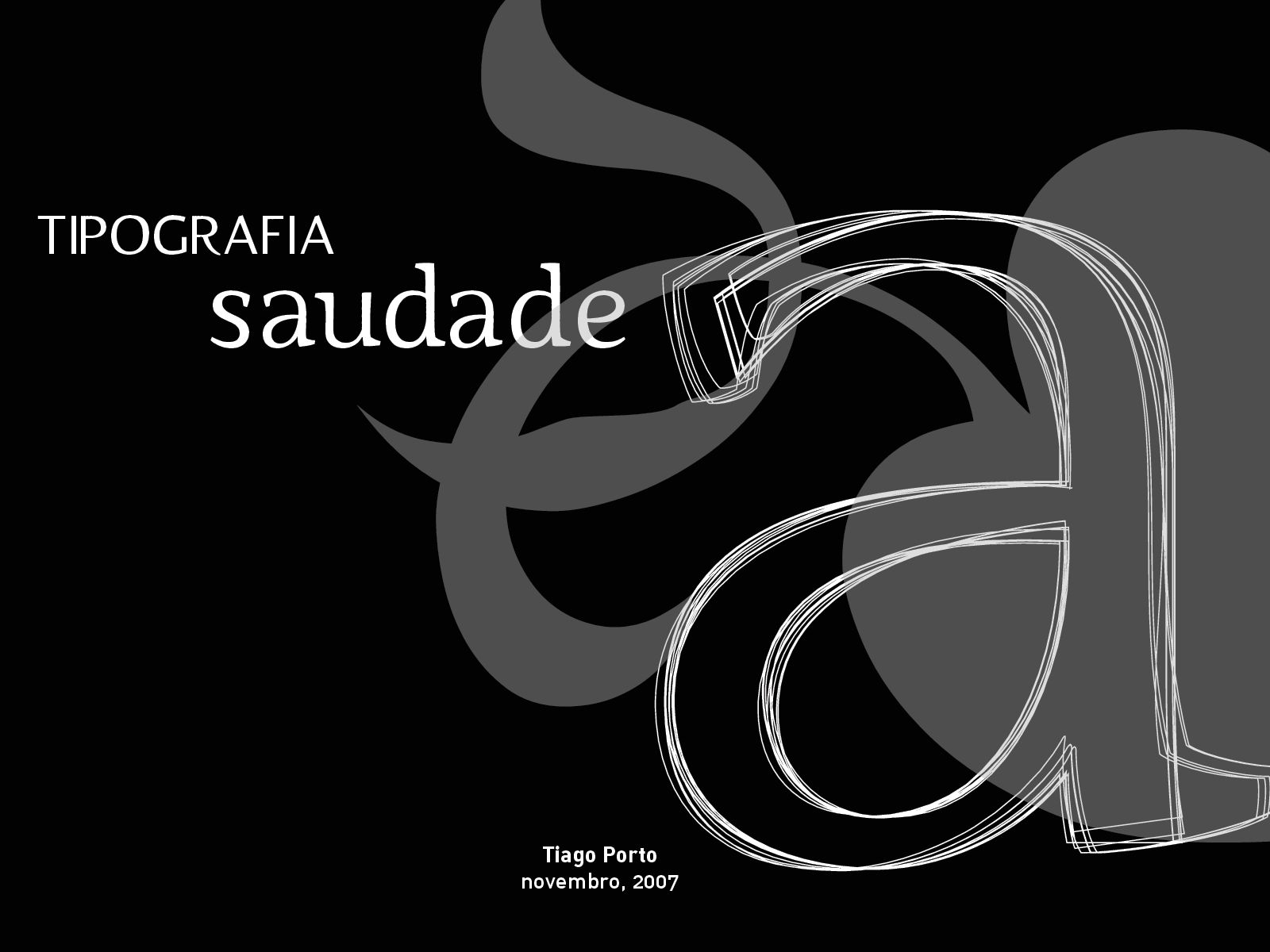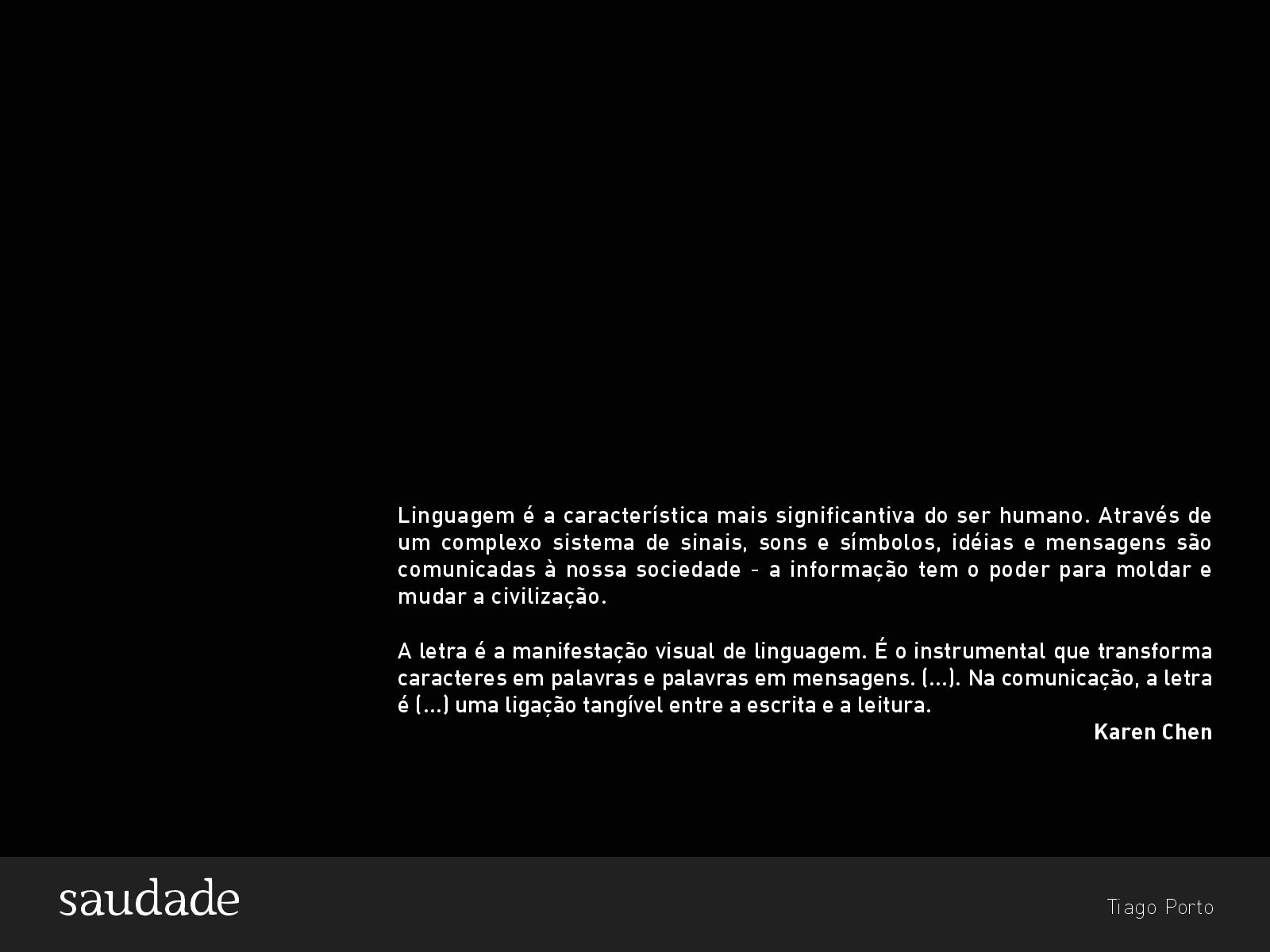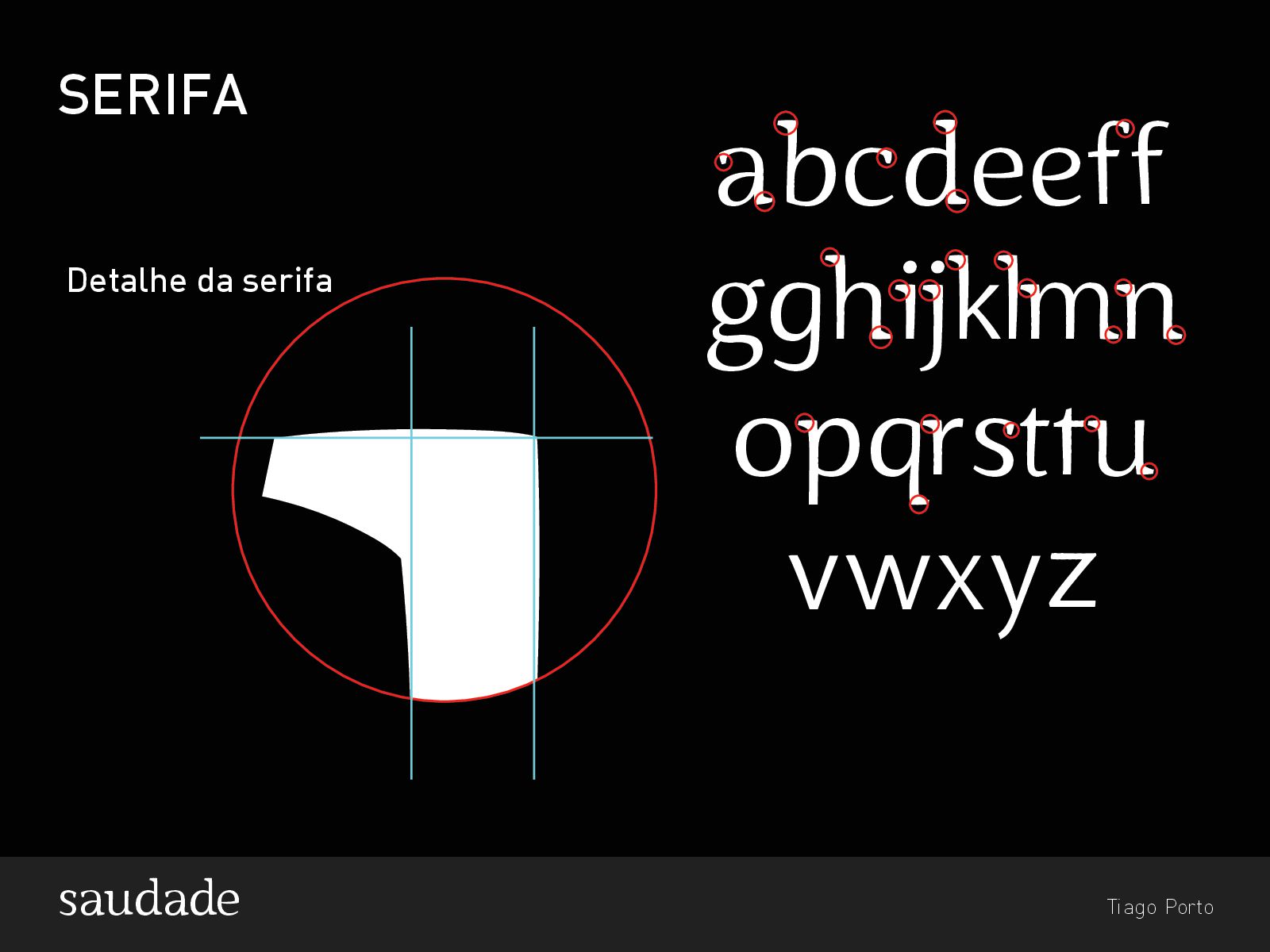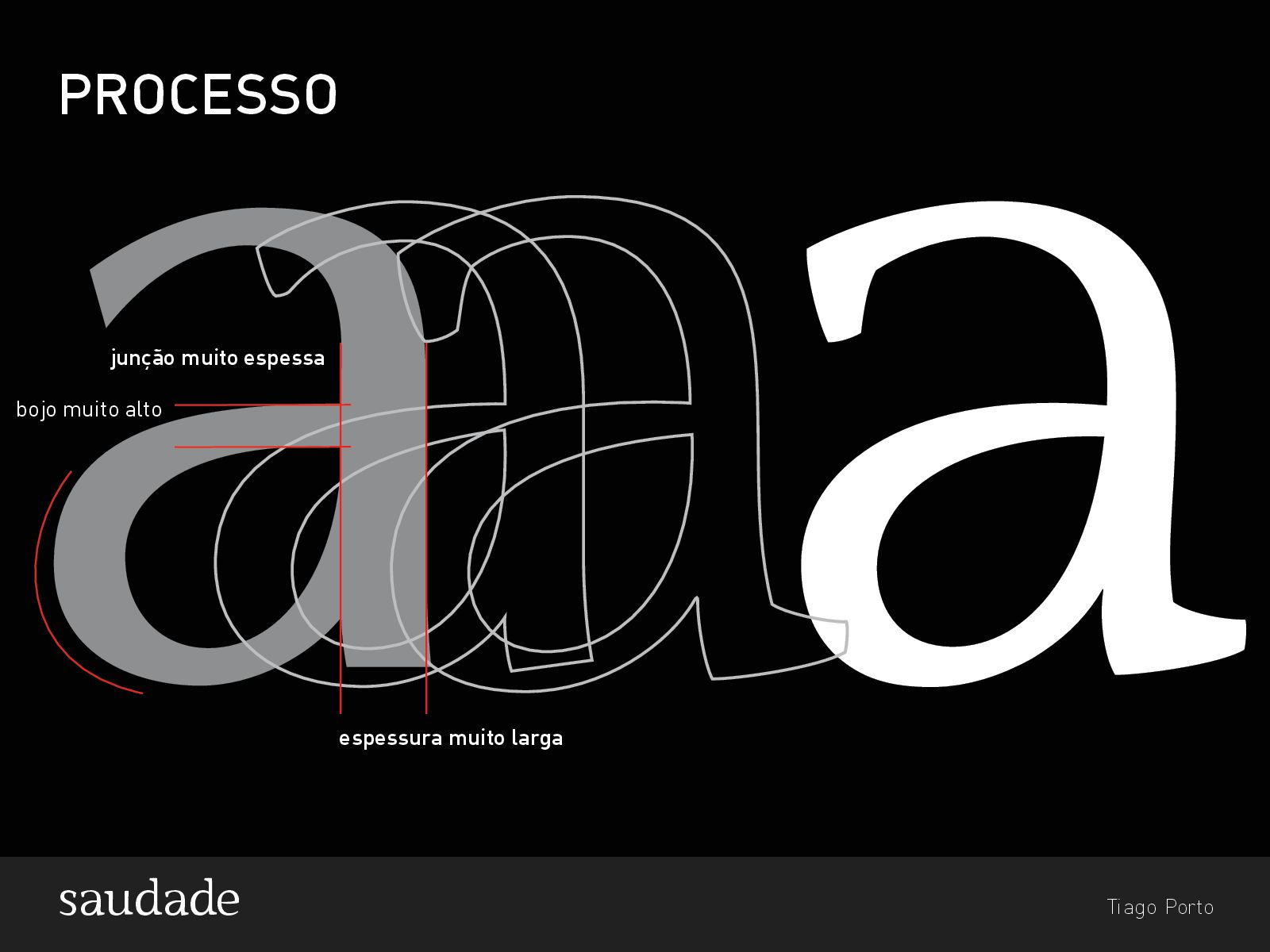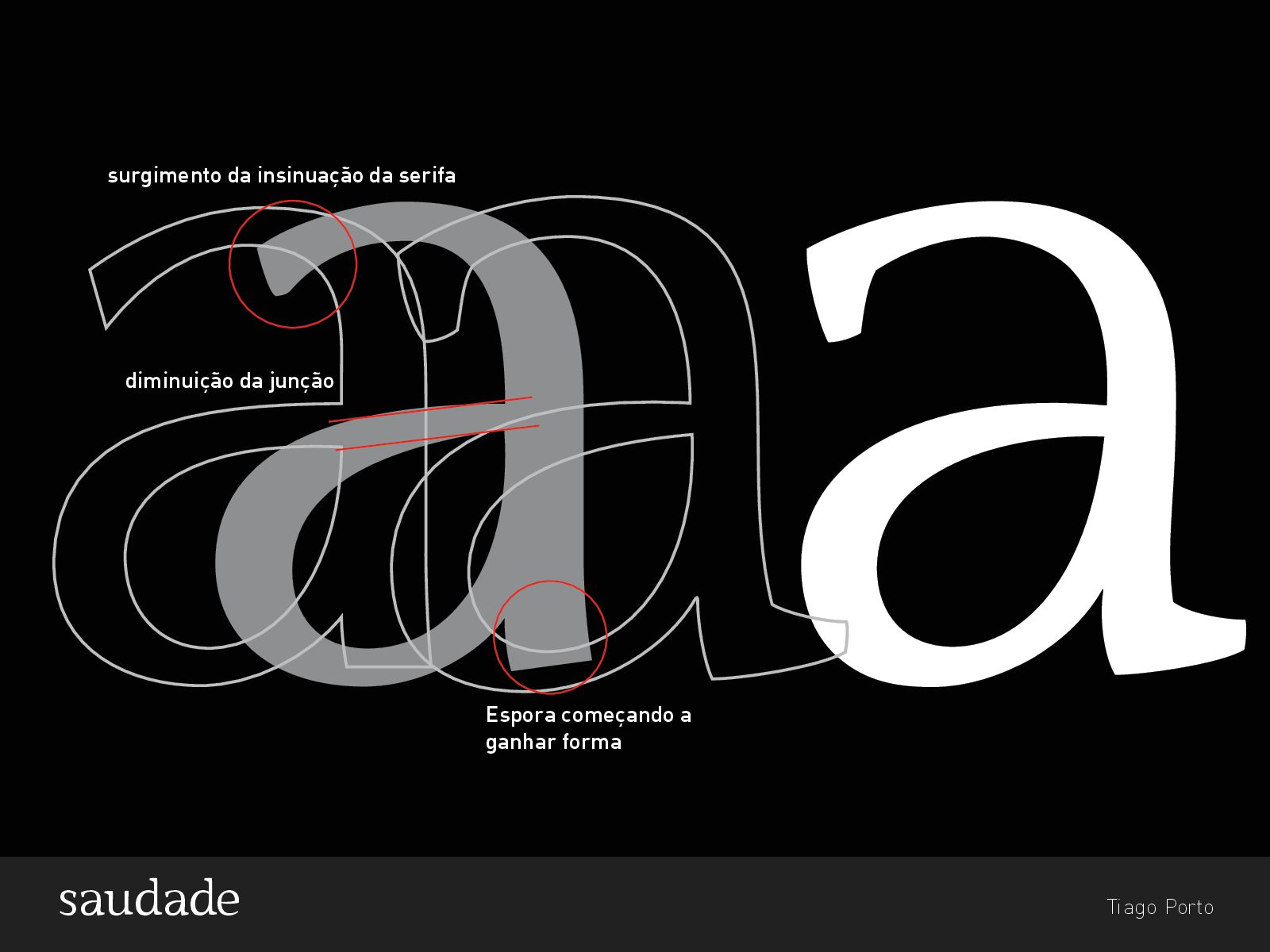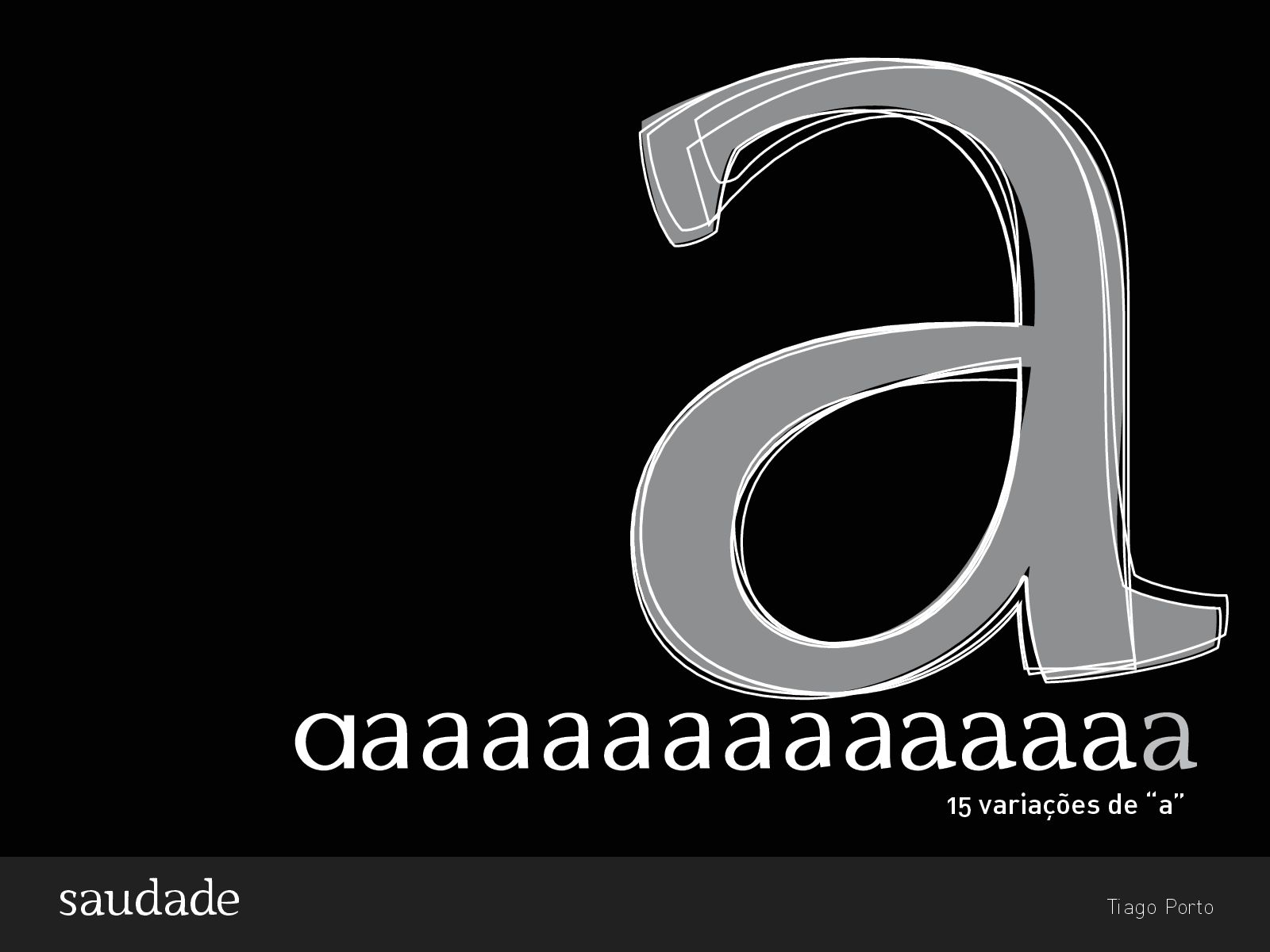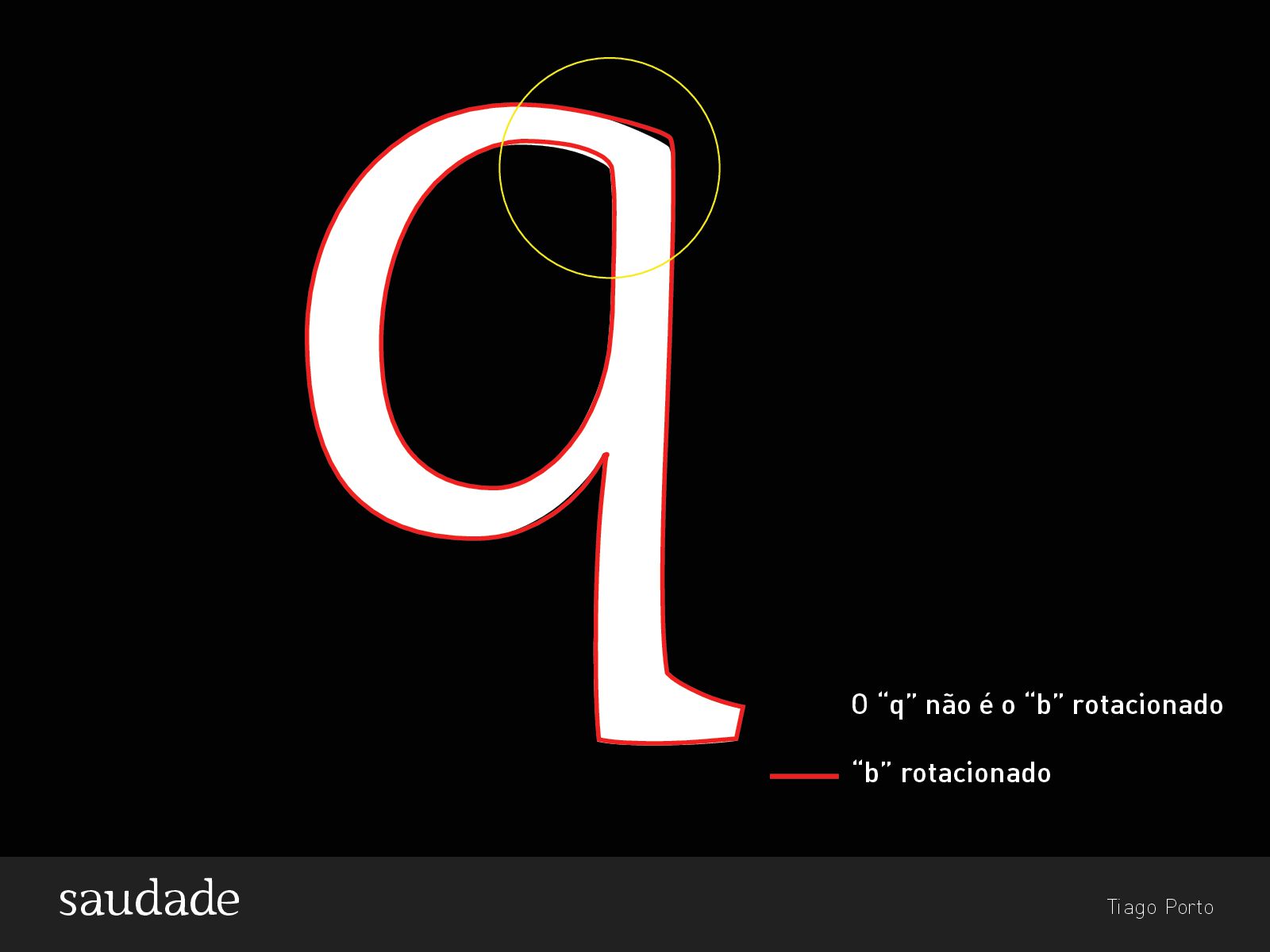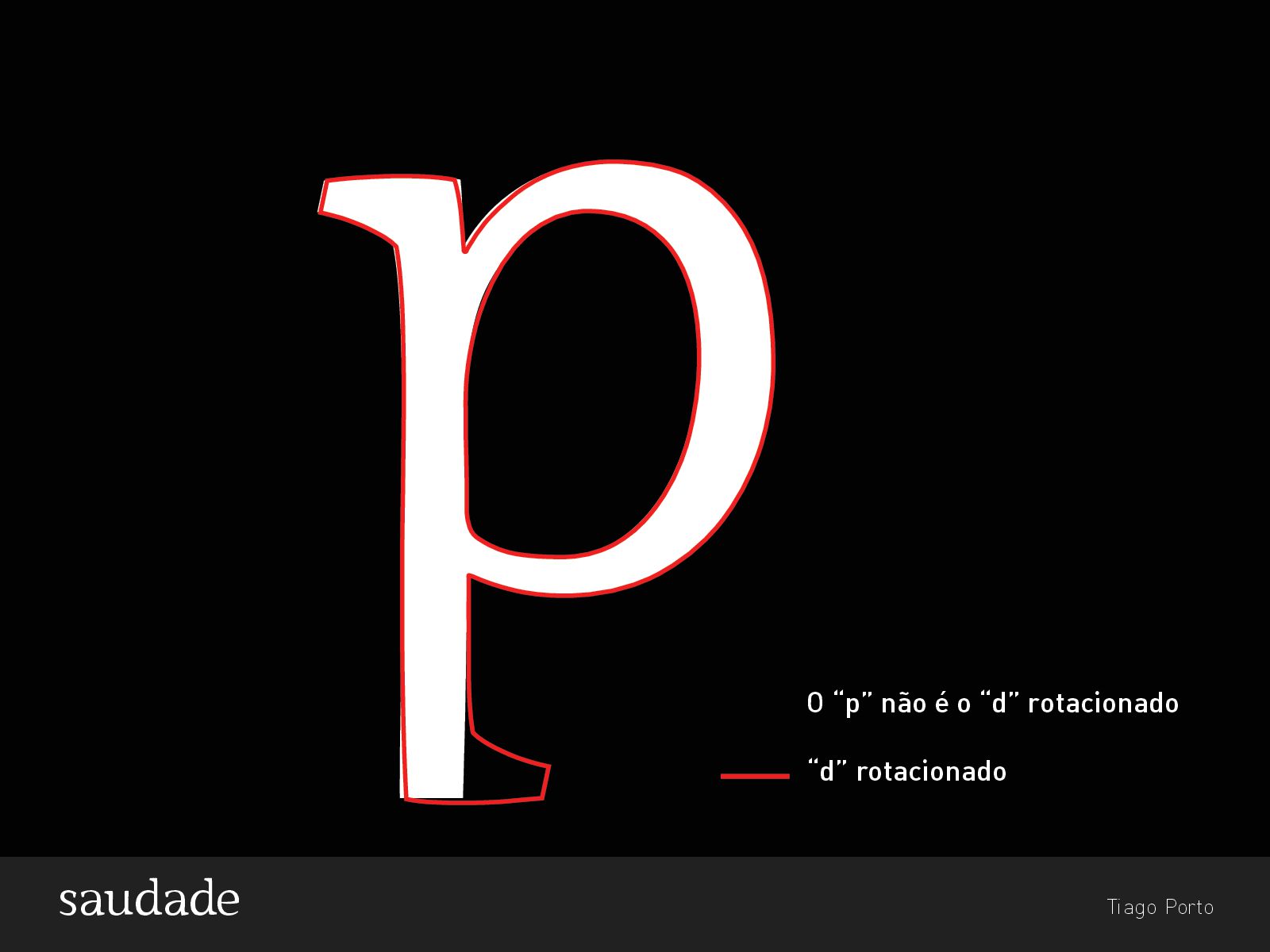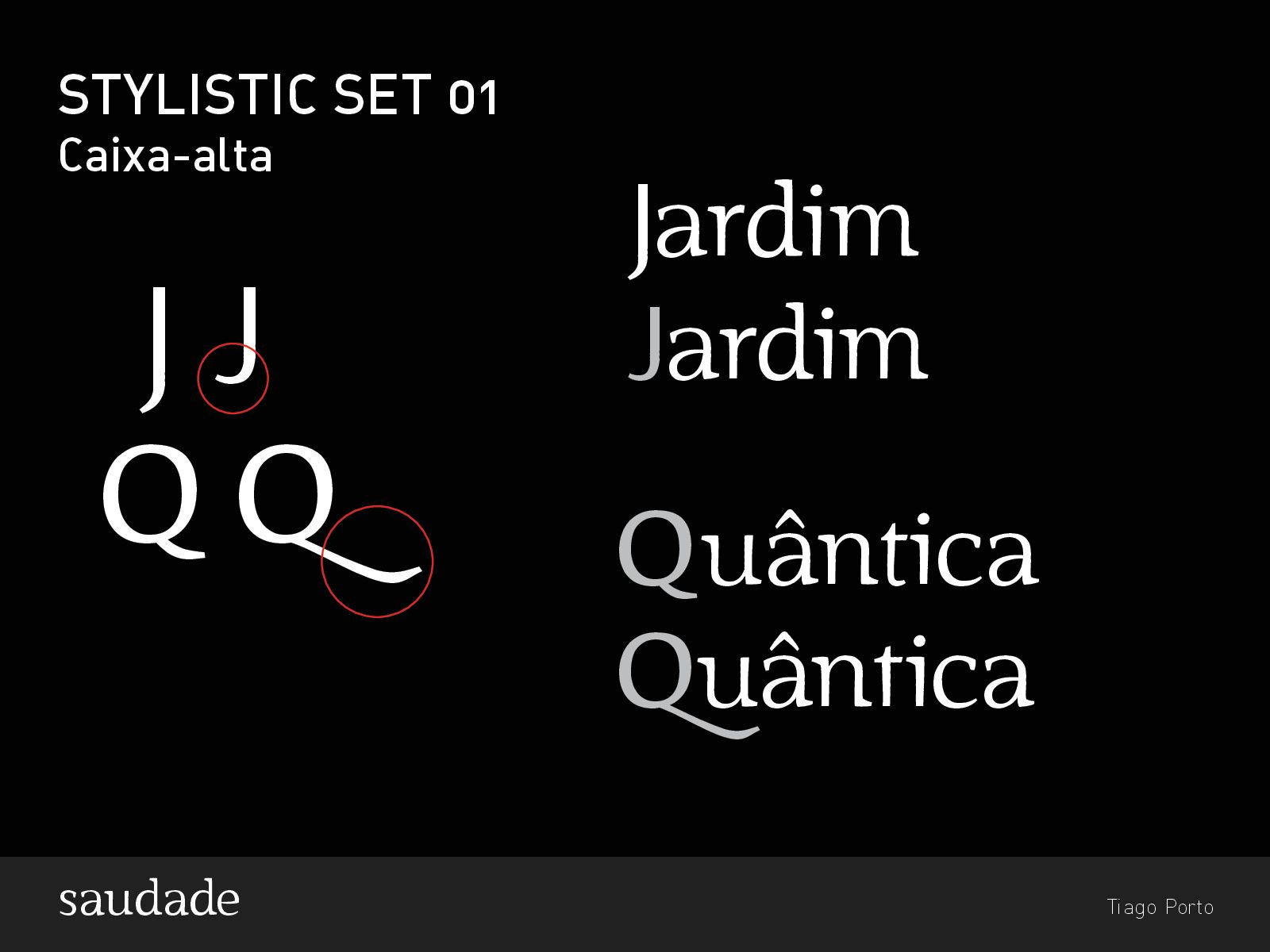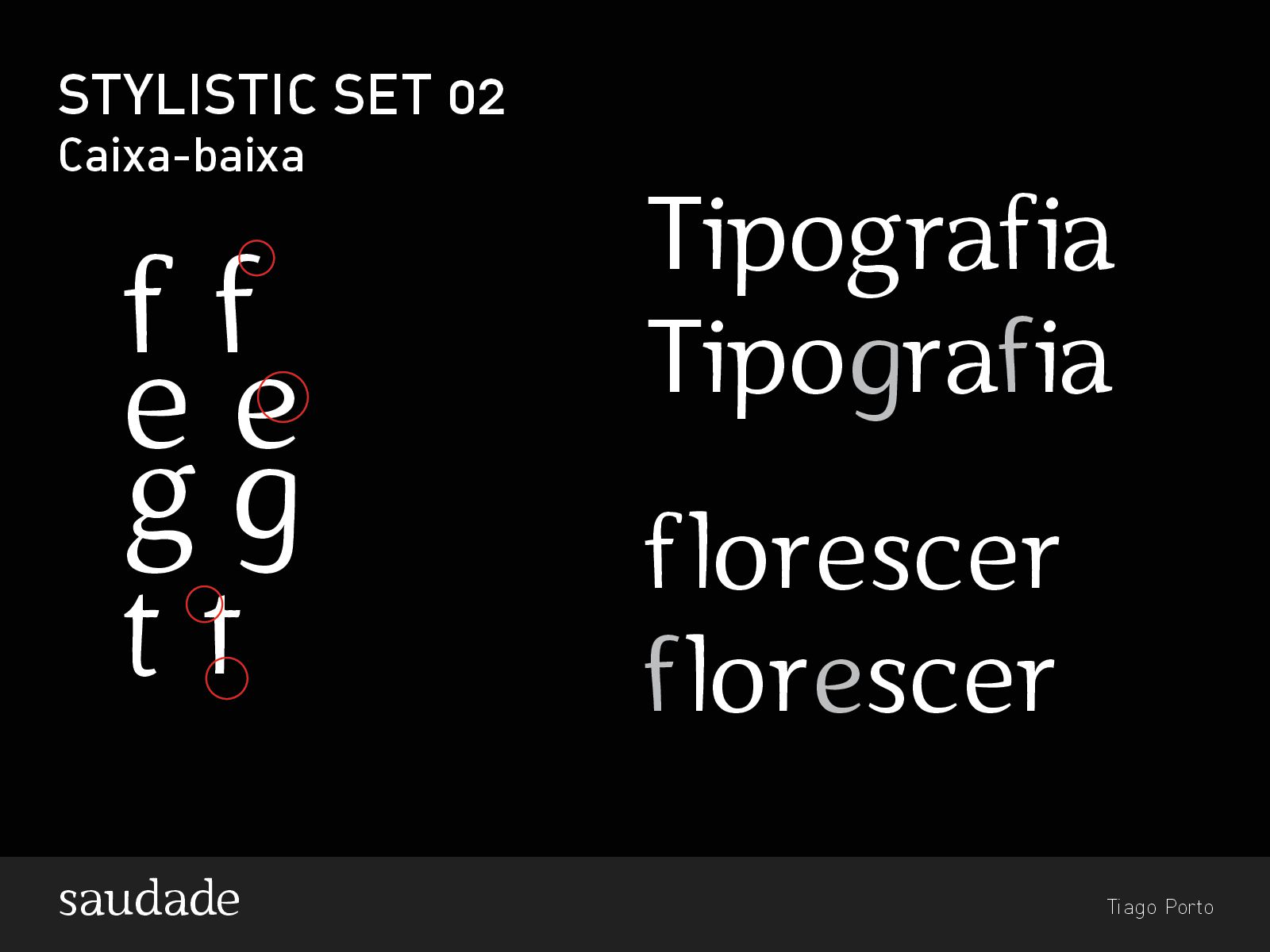
Saudade typeface
1. Tiago Porto saudade Linguagem é a característica mais significantiva do
ser humano. Através de um complexo sistema de sinais, sons e símbolos, idéias e mensagens são comunicadas à nossa sociedade - a informação tem o poder para moldar e mudar a civilização. A letra é a manifestação visual de linguagem. É o instrumental que transforma caracteres em palavras e palavras em mensagens. (...). Na comunicação, a letra é (...) uma ligação tangível entre a escrita e a leitura. Karen Chen
2. Tiago Porto saudade QHxgoaph altura de x Linha de base
Ascendente Descendente caixa-alta PRINCÍPIOS BÁSICOS
3. Tiago Porto saudade Hqx Altura de x um pouco mais
de 2/3 linha onde passa 2/3 linha usada para a construção
4. Tiago Porto saudade Largura das letras Contraste grosso-fino acentuado Eixos
inclinados Adobe Garamond séc XI apO apO Adobe Jenson séc. XV BEBENDO DA “FONTE”
5. Tiago Porto saudade surgimento da serifa mais pronunciada surgimento da
espora (mais parecida com uma serifa) maior incisão espessura diminuída uma curvatura maior do bojo
6. Tiago Porto saudade pqdb Os glifos possuem suas próprias características
mesmo sendo imperceptíveis a tamanhos reduzidos ANATOMIA DOS GLIFOS
7. Tiago Porto saudade q b O “q” não é o
“b” rotacionado “b” rotacionado
8. Tiago Porto saudade p d O “p” não é o
“d” rotacionado “d” rotacionado
9. Tiago Porto saudade aeiou Não basta cada letra funcionar em
separado, elas precisam possuir similaridades para a harmonia do conjunto SIMILARIDADE ENTRE GLIFOS
10. Tiago Porto saudade OPEN TYPE - STYLISTIC ALTERNATES A mais
nova tecnologia de geração de fontes permite implantar programação nos arquivos gerando, assim, inúmeras possibilidades de trocas de glifos automáticos e várias outras mudanças Stylistic Alternates é um dos “features” open type que permite a troca de glifos automaticamente assim que habilitados. Quantum stylistic alternates habilitado possibilitando a troca de glifos
11. Tiago Porto saudade J J Q Q Quântica Jardim
Jardim STYLISTIC SET 01 Caixa-alta
12. Tiago Porto saudade f f e e g g t
t STYLISTIC SET 02 Caixa-baixa Tipografia florescer florescer
13. Tiago Porto saudade &&&& STYLISTIC SET 04, 05, 06 Ampersand
type & language type & language
14. Tiago Porto saudade PORQUE SAUDADE? A necessidade de implementar no
projeto uma cara mais nacional. É percebida uma cultura americanizada no batismo das fontes, independentemente da sua origem. O Brasil possui uma vasta produção de fontes de qualidade que estão sendo consumidas em diversos países e o nome é uma forma de agregar valor e nacionalidade aos projetos trabalhados internamente. Saudade é reconhecidamente uma palavra da língua portuguesa: não há outro verbete que expresse esse sentimento em qualquer outra língua.
15. Tiago Porto saudade Uma lista compilada por uma empresa britânica
(Today Translations) com as opiniões de mil tradutores profissionais coloca a palavra “saudade”, em português, como a sétima mais difícil do mundo para se traduzir. Segundo a diretora da Today Translations, Jurga Ziliskiene, o problema para o tradutor é refletir, com outras palavras, as referências à cultura local que os vocábulos originais carregam. “Provavelmente você pode olhar no dicionário e [...] encontrar o significado”, disse. “Mas, mais importante que isso, são as experiências culturais [...] e a ênfase cultural das palavras.” Lista 1. “Ilunga” (africano tshiluba) 2. “Shlimazl” (ídiche, língua germânica falada por judeus) 3. “Radioukacz” (polonês) 4. “Naa” (japonês) 5. “Altahmam” (árabe) 6. “Gezellig” (holandês) 7. Saudade (português) 8. “Selathirupavar” (tâmil, língua falada no sul da Índia) 9. “Pochemuchka” (russo) 10. “Klloshar” (albanês) PESQUISA
16. Tiago Porto saudade A tipografia existe para honrar seu conteúdo
Assim como a oratória, a música, a dança, a caligrafia - como tudo que empresta graça à linguagem, a tipografia é uma arte que pode ser deliberadamente mal utilizada. É um ofício por meio do qual os significados de um texto (ou sua ausência de significado) podem ser clarificados, honrados e compartilhados, ou conscientemente disfarçados.(...) A melhor tipografia é uma forma visual de linguagem que liga atemporalidade ao tempo(...). Um dos princípios da tipografia durável é, sempre, a legibilidade. Mas há um outro. Trata-se de um interesse, merecido ou não, que doa sua energia vital à página. Robert Bringhurst